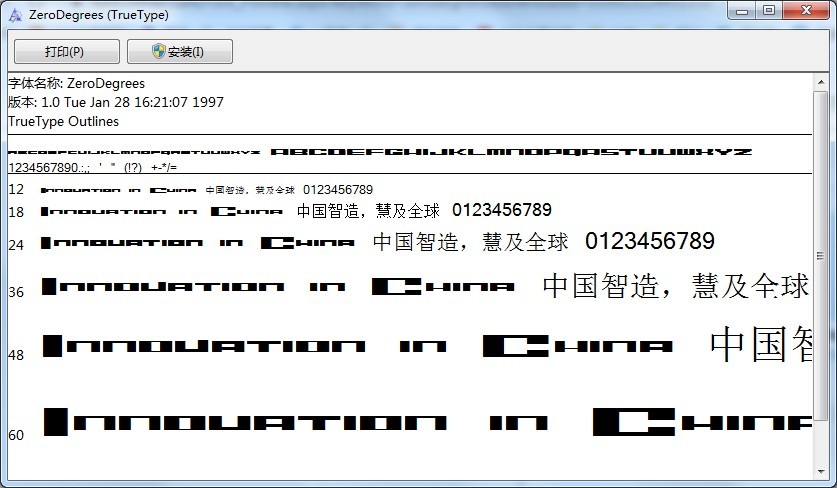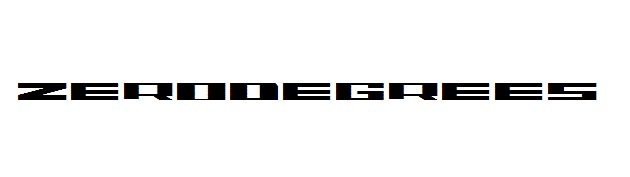
zerodegrees ttf版字體風(fēng)格十分獨(dú)特的一款英文字體,字體整體較為扁平,識(shí)別度高。該字體更適用于英文簽名或是其它方面的設(shè)計(jì)當(dāng)中,整體豐富藝術(shù)感強(qiáng),感興趣的朋友可以來(lái)下載使用。
zerodegrees是用于創(chuàng)意設(shè)計(jì)方面的字體。
字體名稱:zerodegrees